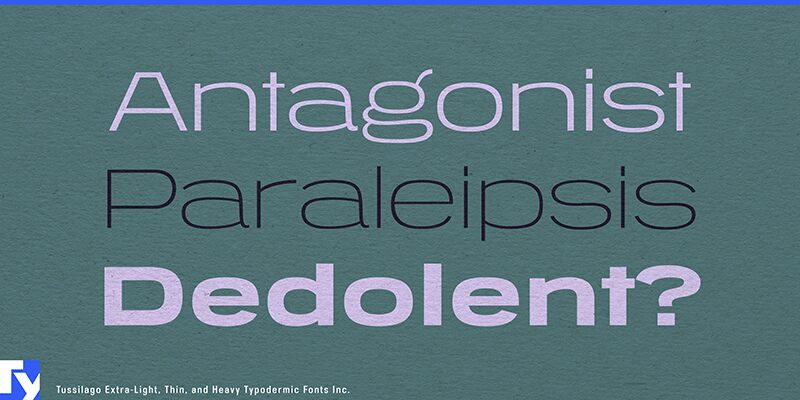
Tussilago est une police sans sérif large, avec un pied dans le milieu du XXe siècle et l'autre solidement ancré dans le présent. Ses lettres aux proportions étendues rappellent l'assurance des polices de titrage d'époque, tandis que des détails subtils et un espacement moderne la rendent parfaitement adaptée aux créations contemporaines. Des chiffres elzéviriens et alignés sont intégrés, vous permettant d'ajuster avec précision le ton de vos projets, des maquettes éditoriales aux identités de marque. Grâce à sa clarté et au dessin ouvert de ses glyphes, Tussilago se prête aussi bien aux titres percutants qu'aux blocs de texte compacts.